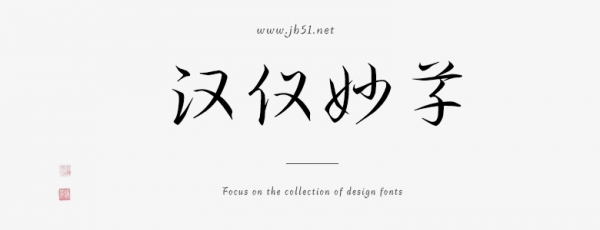
漢儀妙草W是由漢儀字庫出品,字體瀟灑寫意,逸趣橫生,頗具草書簡約之美,排版工整而富于變化,書法字帖等領(lǐng)域,需要的朋友可以前來本站下載。
漢儀妙草這款字是根據(jù)現(xiàn)行字庫字體的設(shè)計標準進行制作的,嚴格意義上來講不算作純粹的草書。在設(shè)計中借用了很多草法,但同時也兼有許多行書的處理方式,不管是簡繁寫法的區(qū)分,還是為防止混淆所做的不同部首、部件寫法的區(qū)分,以及為了兼顧一定識別性所做的寫法上的篩選等,都沒有完全符合草書的要求。這些也都是為了保證這款字更加符合當代環(huán)境下的使用需求所做的必要的取舍。
作為一款具有實驗性和開創(chuàng)性的字體,漢儀妙草瀟灑寫意,逸趣橫生,頗具草書簡約之美,排版工整而富于變化,適合應(yīng)用于文化藝術(shù)場景,如展覽海報、書籍畫冊等。推薦與宋體搭配使用,在增強易讀性的同時更能突出漢儀妙草的飄逸。
漢儀妙草的字面小而靈動,中宮舒展,重心平穩(wěn)。字字獨立而不相連,結(jié)體簡約,清晰可辨。